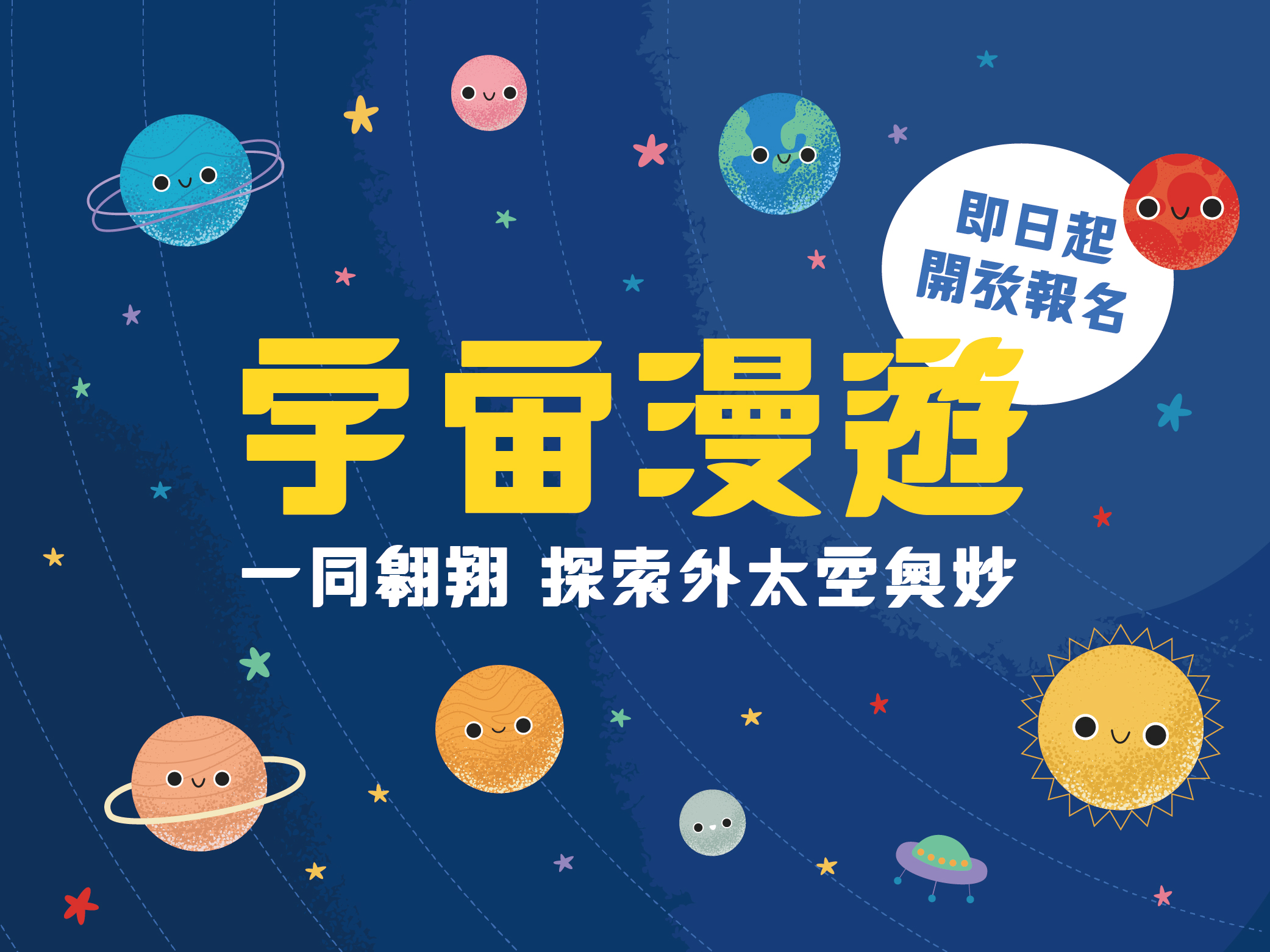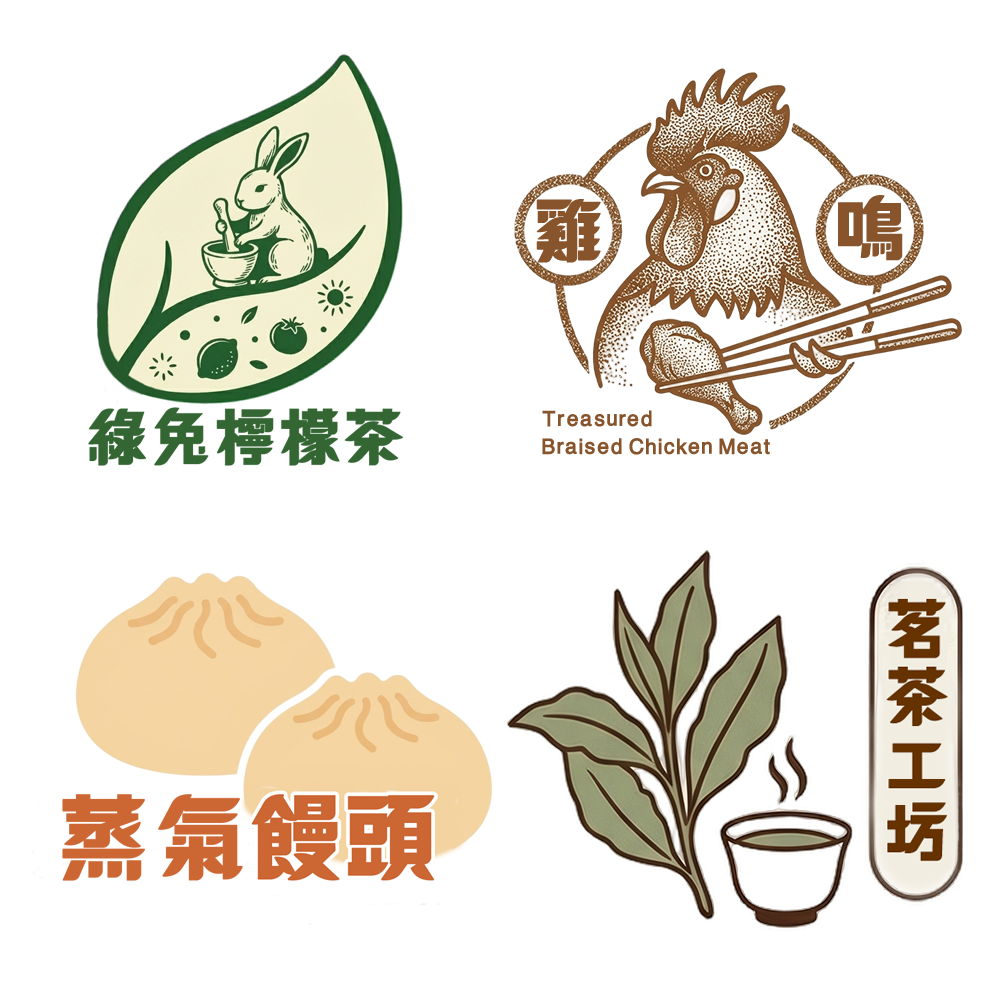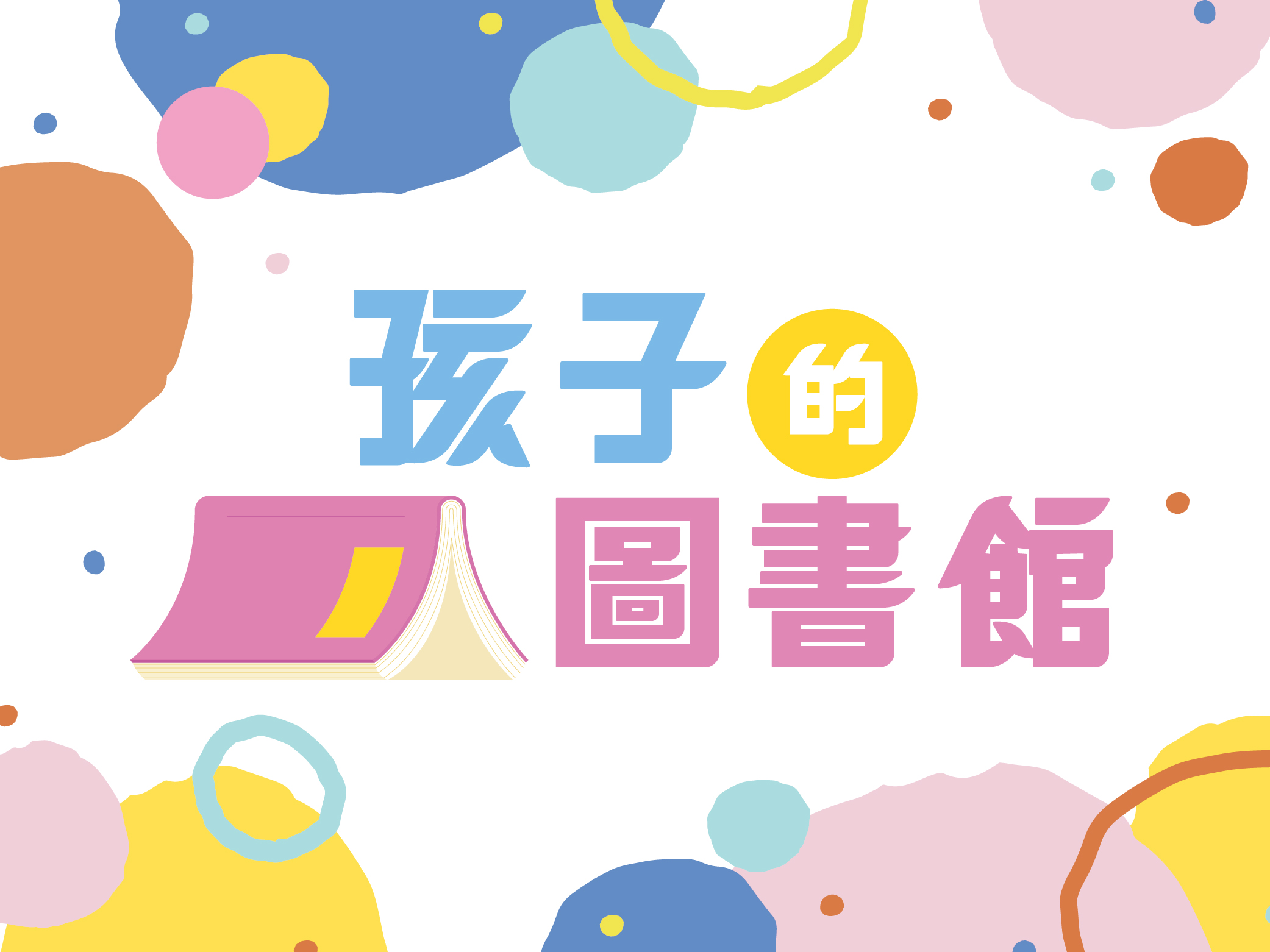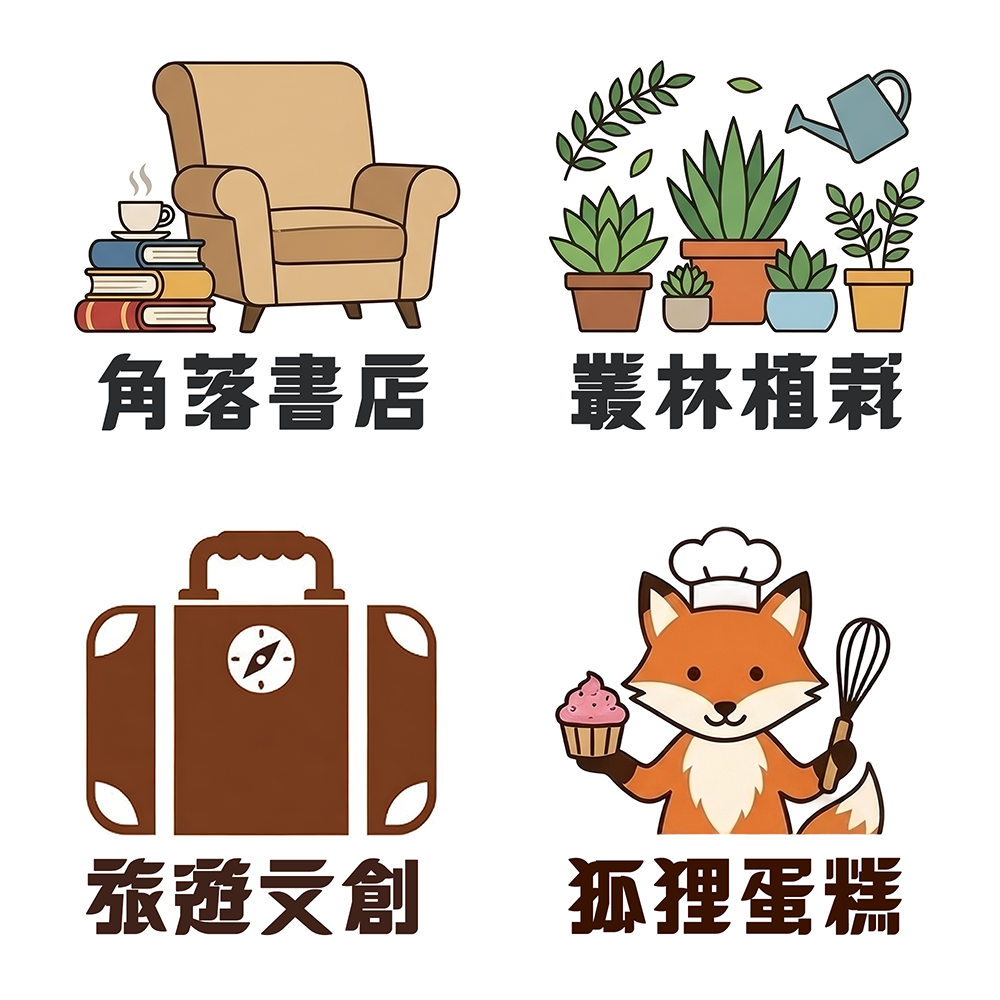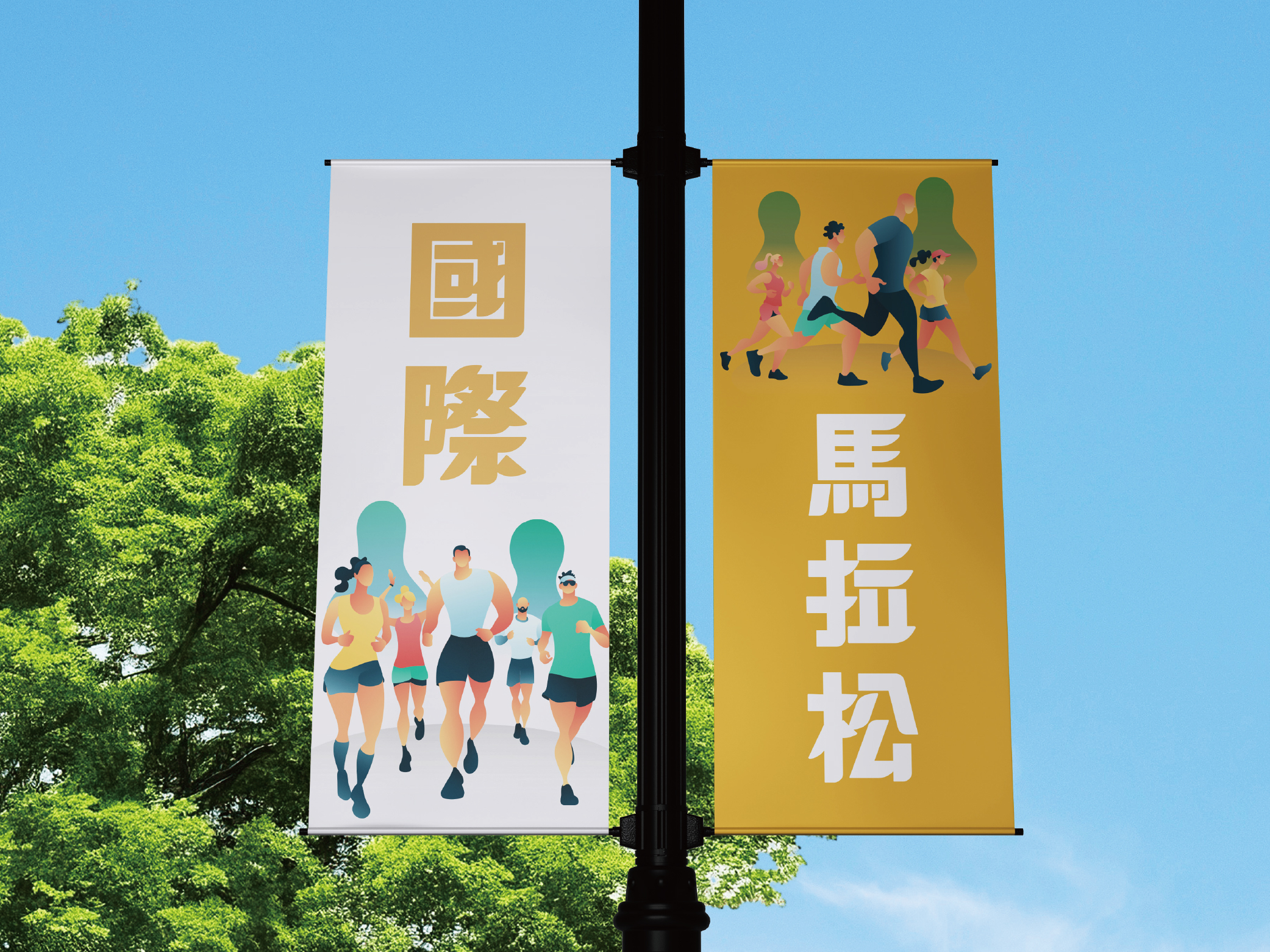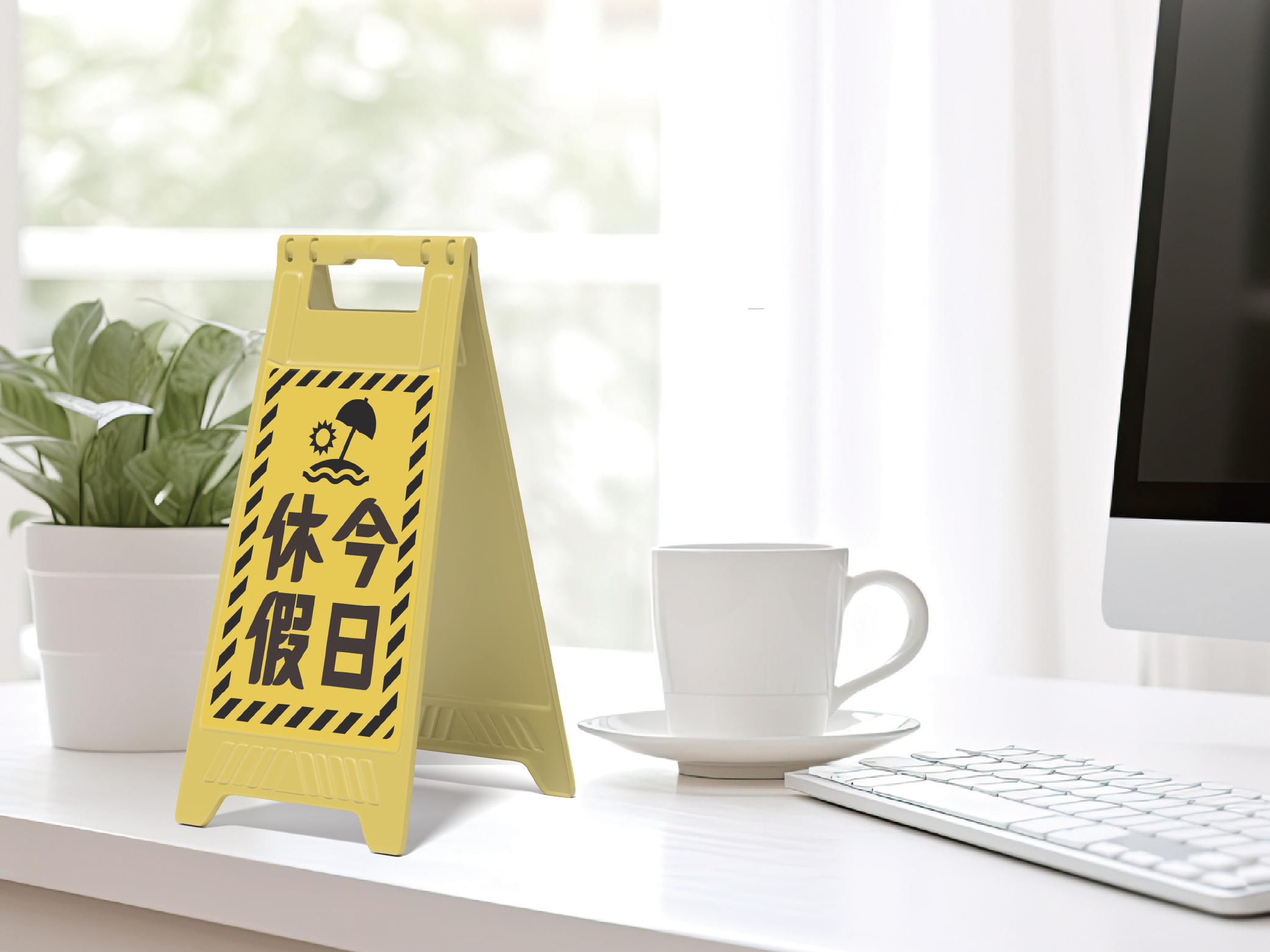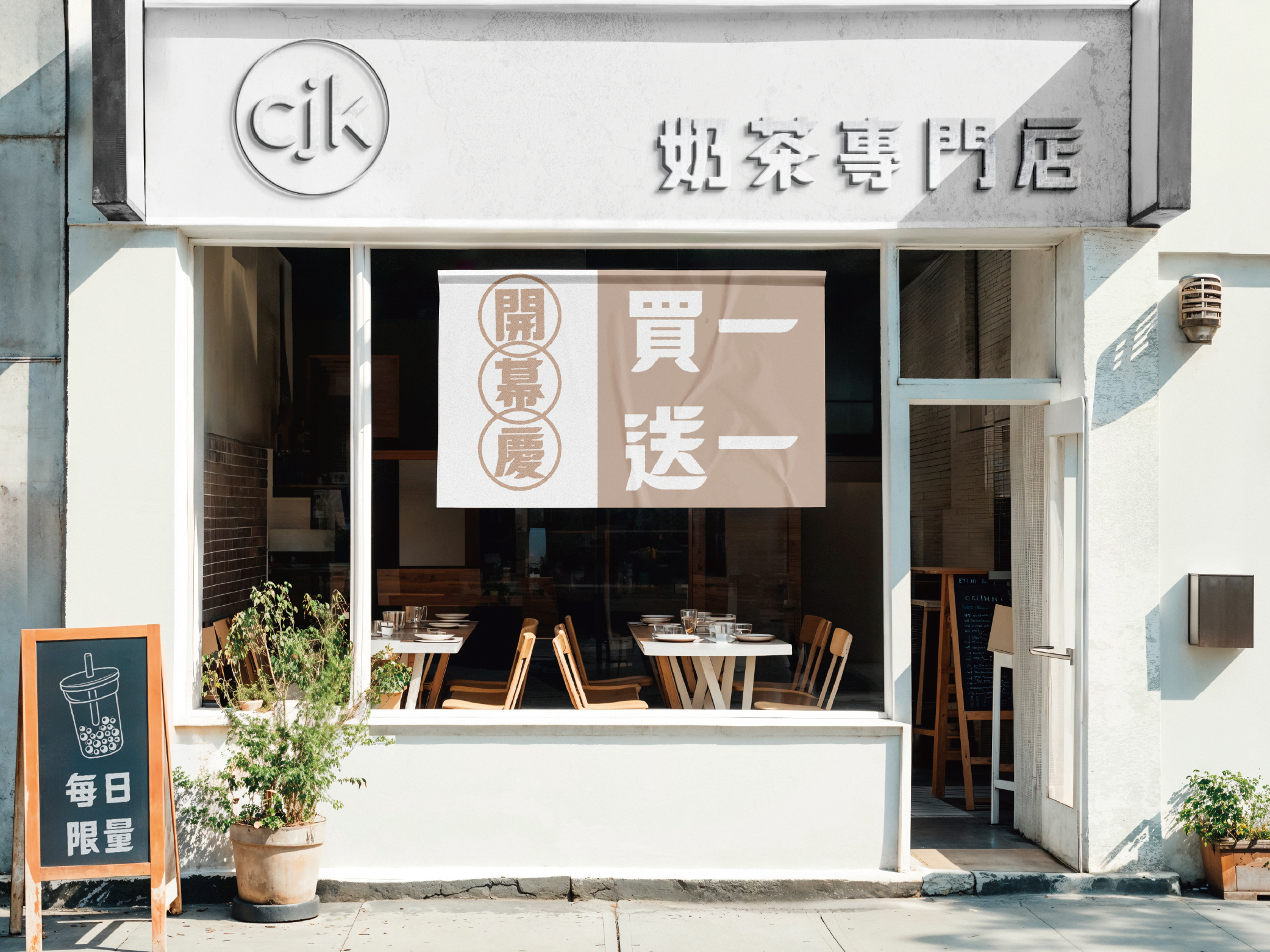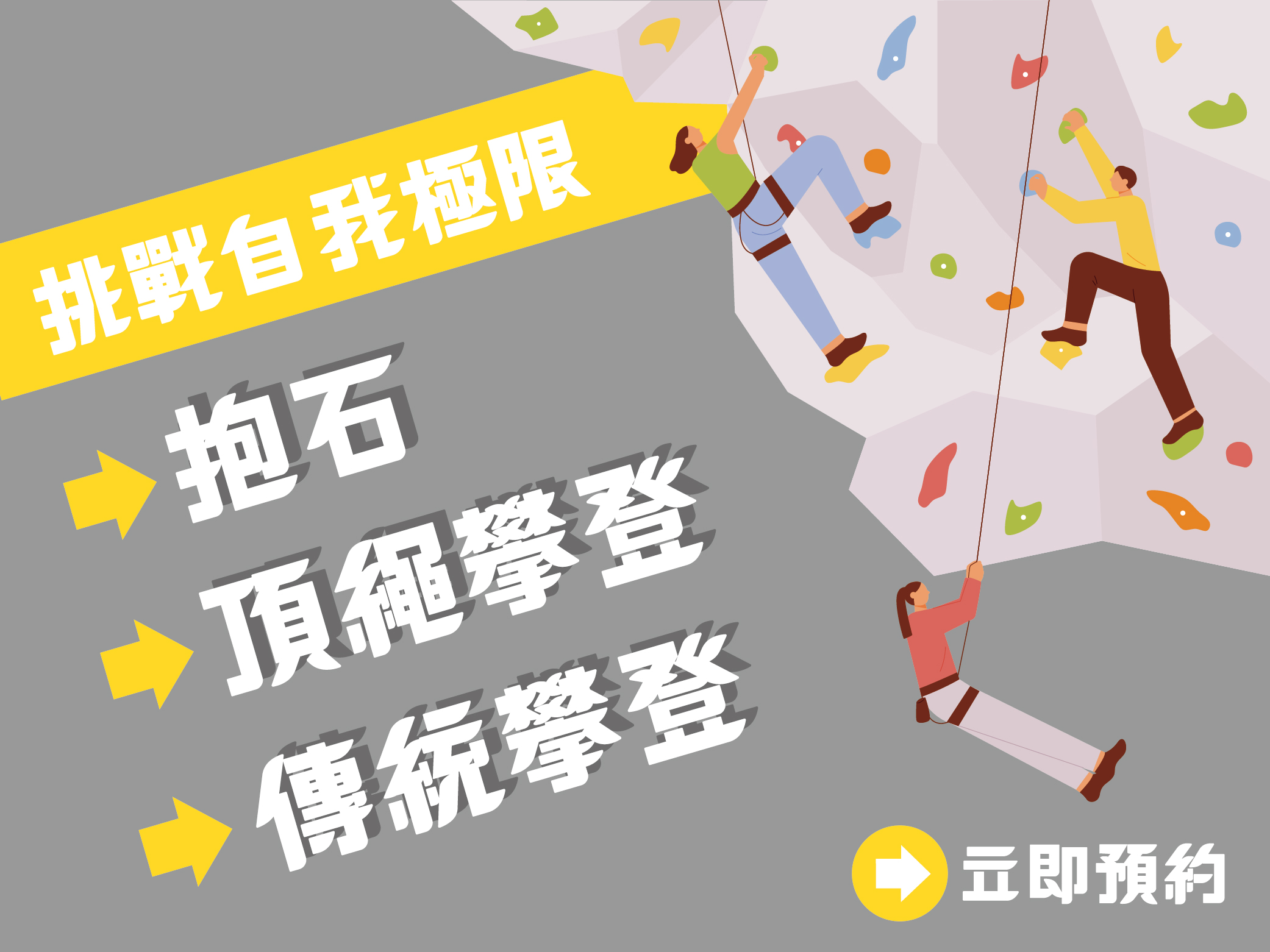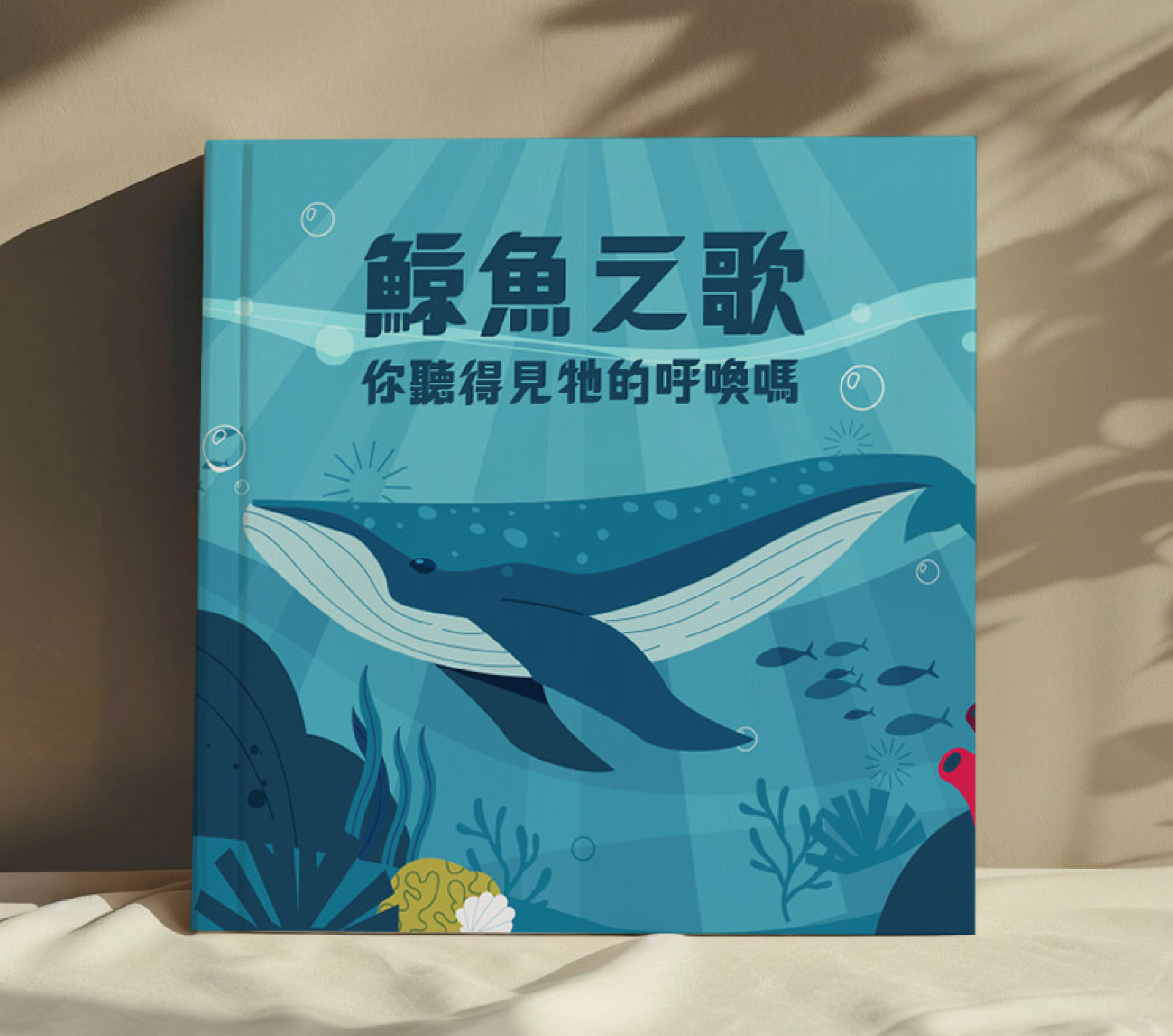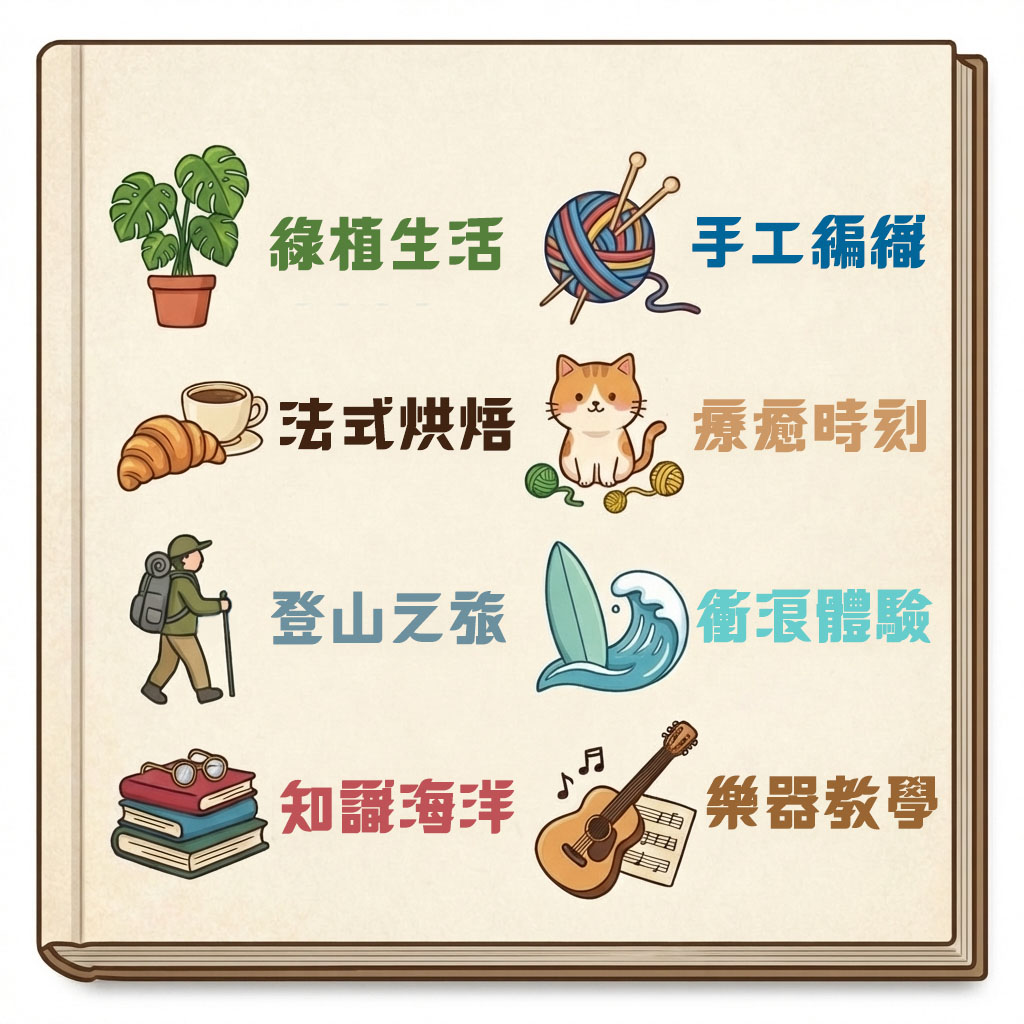
樂藝體大約有15800個字(包括歐文、數字、符號)
樂藝體 - 讓創意在厚實間,流露快樂的筆觸
樂藝體為平面設計師提供現時流行的極粗字體另類選擇。此字體橫直斜的筆劃雖然有著相若的粗度,但卻能保持易看易明,全因橫劃以彎刀收尾,此亦是本字體的特質,給予讀者快樂的感覺。
1. 均勻筆劃,不失張力
樂藝體的橫、直、斜筆劃均維持相若的厚實粗度。這種高飽和度的視覺表現,能讓您的標題在第一時間奪取視線,展現無與倫比的品牌份量感。
2. 彎刀收尾:字體的快樂密碼
這是「樂藝體」最具辨識度的特質。我們在每一處橫劃的末端,精緻地勾勒出如「彎刀」般的收尾曲線。這個微小的設計不僅消解了粗線條的厚重感,更賦予了字體一種躍動的生命力,讓觀者感受到如沐春風的快樂情緒。
3. 極致易讀,一眼入魂
極粗字體最怕「糊成一團」。透過精確的空間佈局與彎刀收尾帶來的留白感,樂藝體在維持極高粗度的同時,依然能保持易看、易明的視覺高度,確保訊息傳遞精準無誤。